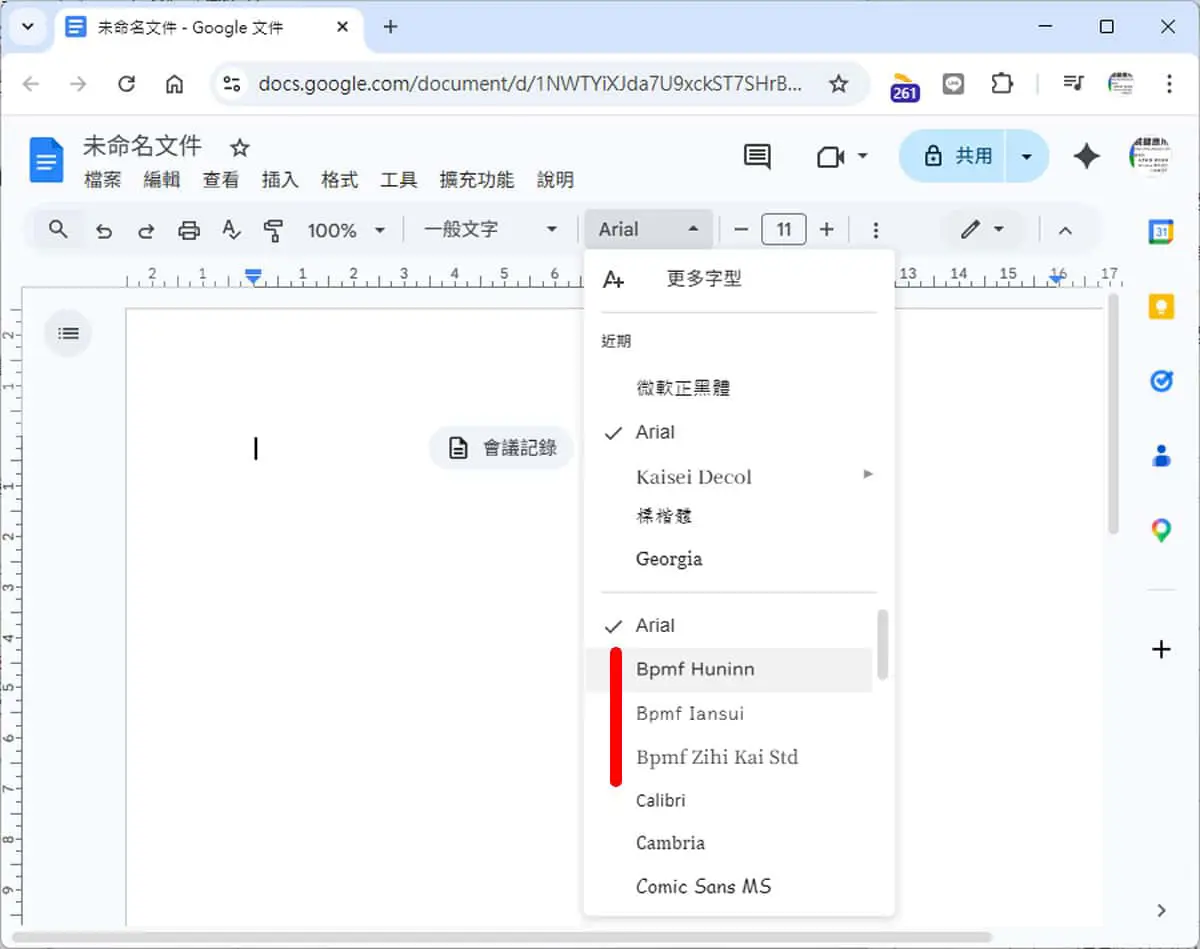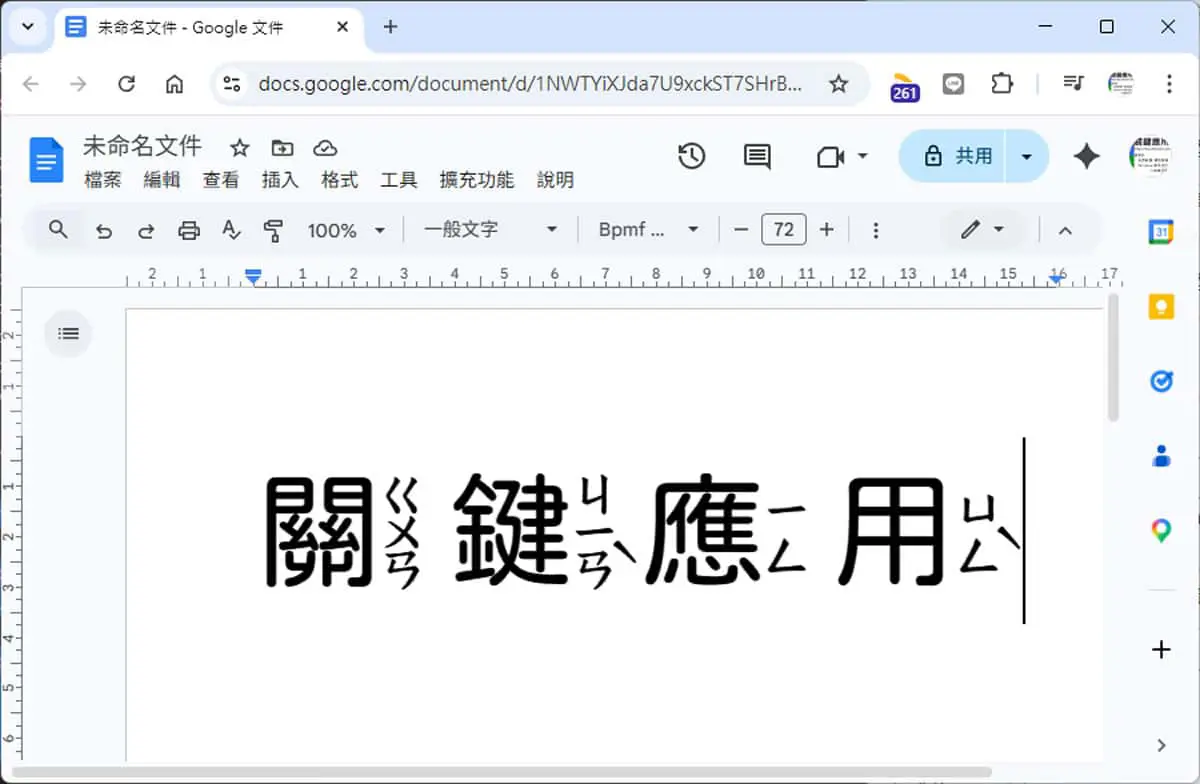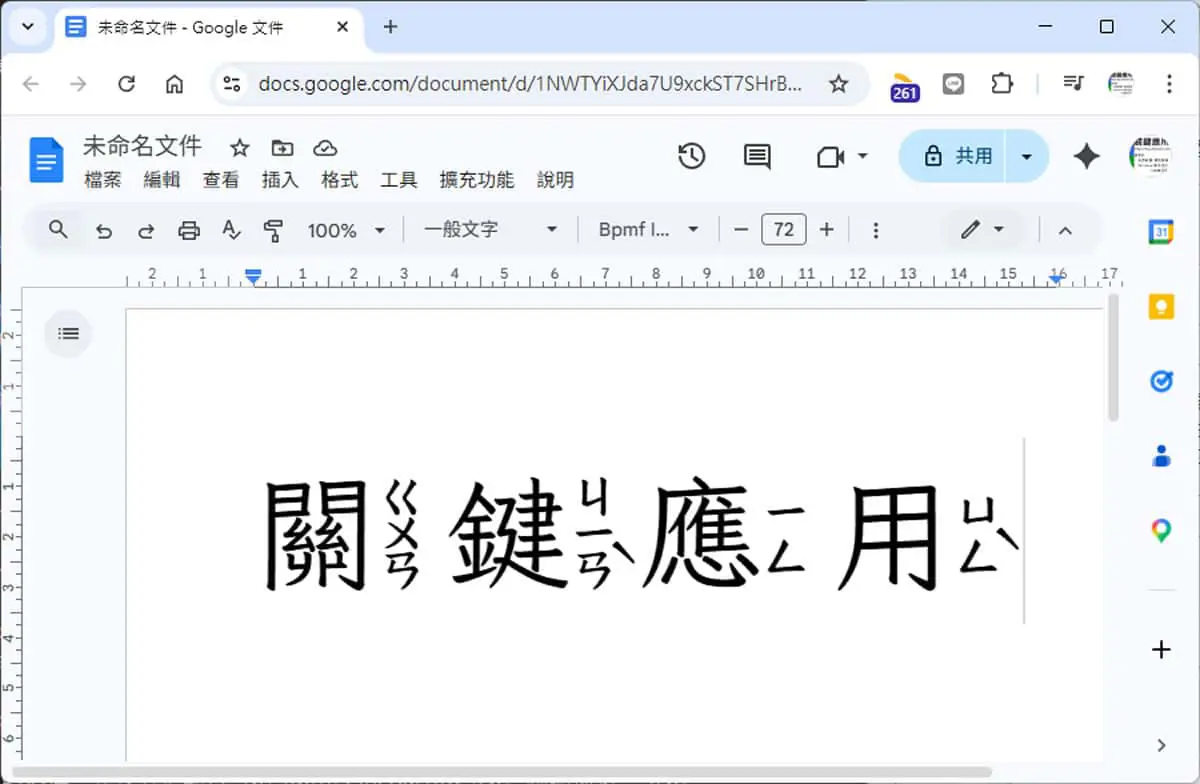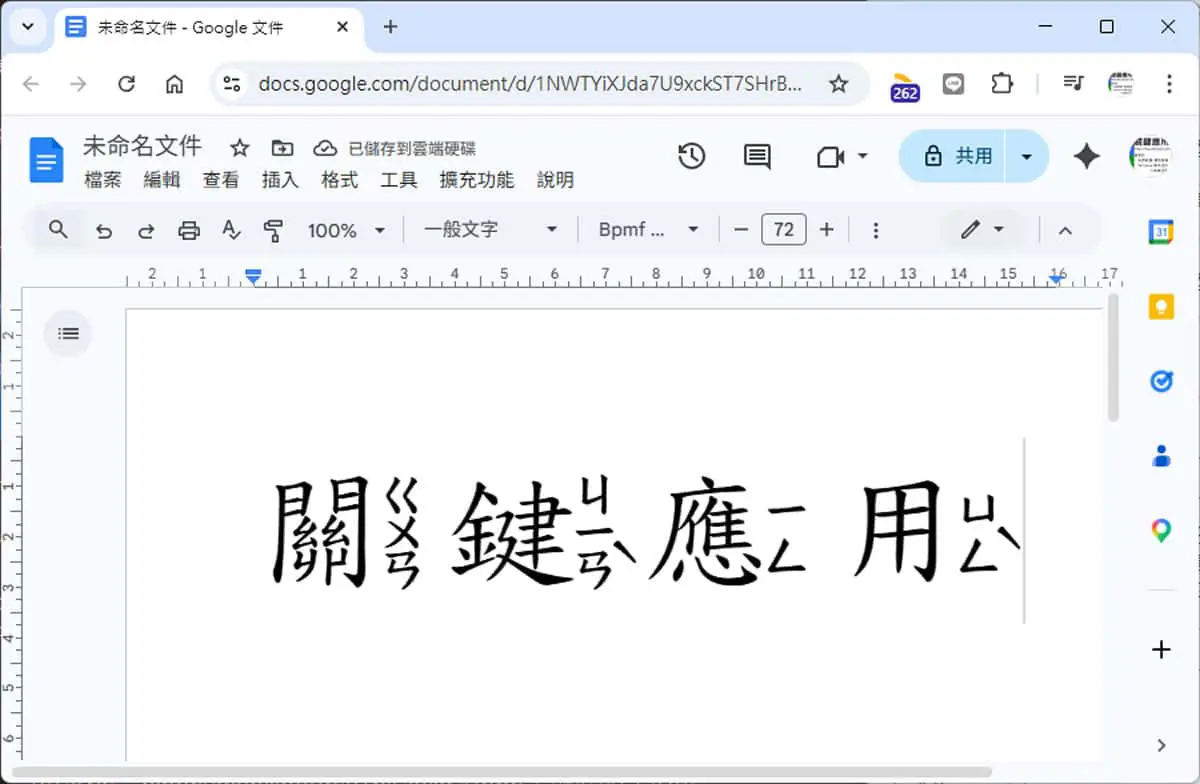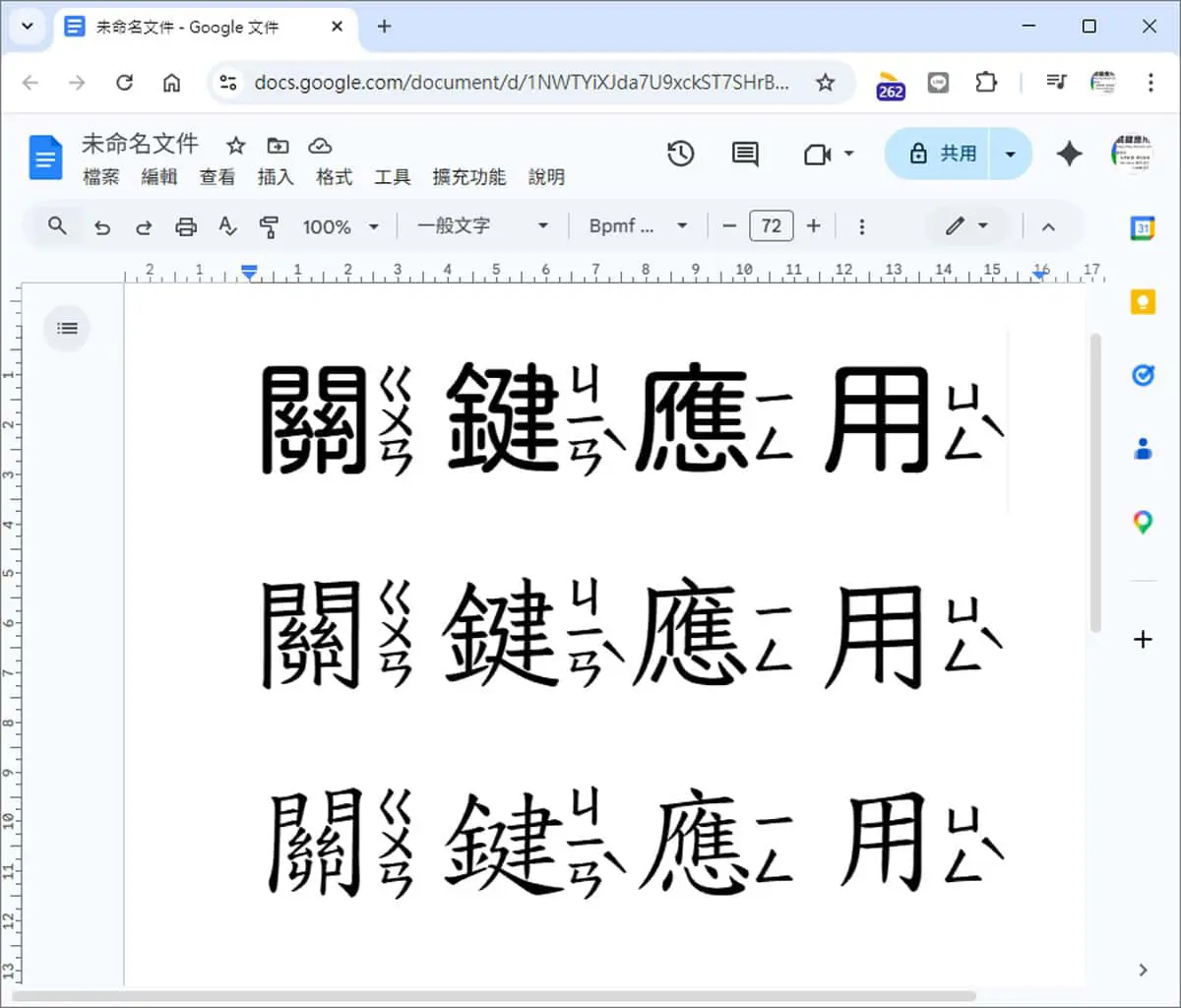
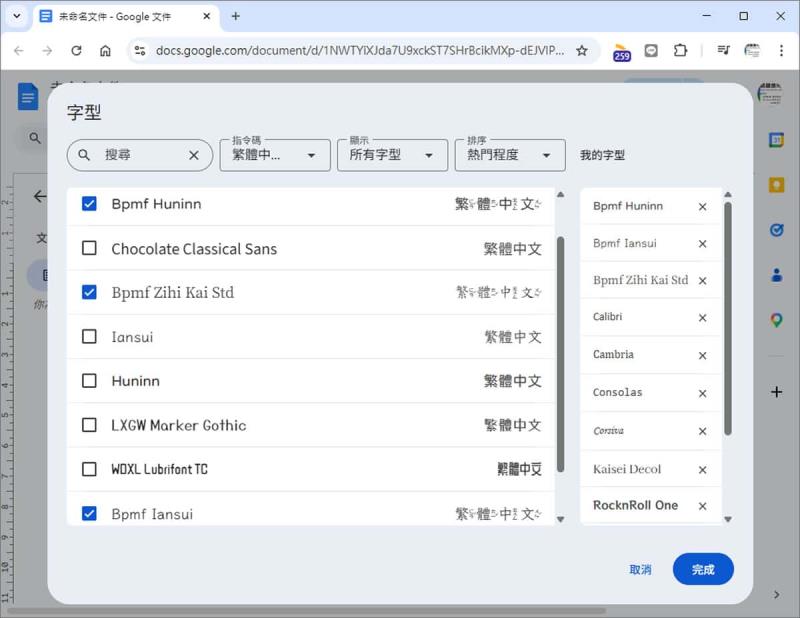
想在 Google 文件裡用注音字型,卻不知道從哪裡找起?其實完全不需要安裝任何外掛,Google 文件字型庫裡就內建了 3 款免費的繁體中文注音字型,這篇文章帶你一步一步把它們全部加進來。
對老師或家長來說,在 Google 文件裡打注音是很常見的需求,尤其是製作低年級教材、拼音練習卷的時候。很多人第一個念頭是「去找外掛」,實際上根本不需要,因為 Google 字型庫裡早就有現成的注音字型可以用。這次整理出來的 3 款,全部都支援繁體中文與注音符號,直接從 Google 文件裡新增就好。
第一款:Bpmf Huninn(粉圓注音體)
粉圓注音體是這三款裡外觀最圓潤可愛的一款,字體造型圓圓的、筆畫飽滿,適合低年級教材或親子互動的文件使用。對小朋友來說,這種字型看起來比較活潑,不像正楷那麼嚴肅,閱讀起來也比較輕鬆。在搜尋框輸入 Bpmf Huninn 就能找到它。
第二款:Bpmf Iansui(芫荽注音體)
芫荽注音體的風格比粉圓更接近手寫感,筆畫帶有一點自然的彈性,整體看起來清爽又有個性。這款字型對於想製作有溫度、不太制式的教學講義的老師來說,會是不錯的選擇。在搜尋框輸入 Bpmf Iansui 即可找到。
第三款:Bpmf Zihi Kai Std(字嗨注音體)
字嗨注音體是三款中最接近標準楷書的字型,筆畫工整、結構嚴謹,注音符號的位置也標準清楚。對需要製作正式教材、考卷或標準化學習單的老師來說,這款是最合適的選擇。在搜尋框輸入 Bpmf Zihi Kai Std 就能找到。
三款字型怎麼選?一張表看清楚
| 字型名稱 |
中文名稱 |
風格特色 |
適合用途 |
| Bpmf Huninn |
粉圓注音體 |
圓潤飽滿、活潑可愛 |
低年級教材、親子文件 |
| Bpmf Iansui |
芫荽注音體 |
手寫感、清爽有個性 |
講義、非正式教學素材 |
| Bpmf Zihi Kai Std |
字嗨注音體 |
標準楷書、工整嚴謹 |
正式教材、考卷、學習單 |
總結
Google 文件要加注音字型,真的不需要裝任何外掛,只要善用內建的「更多字型」功能,搜尋 Bpmf 開頭的字型名稱,3 款注音字型就能全部加進來。粉圓適合活潑風、荽適合手寫感、字嗨適合正式教材,依照需求選一款就好。下次做教材,直接在 Google 文件裡搞定!